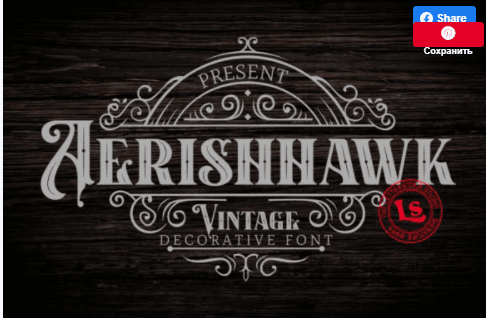
Aerishhawk Font
Aerishhawk - это смелый, отчетливый и невероятно впечатляющий дисплейный шрифт. Добавьте его к каждому дизайну, который требует напористой и элегантной атмосферы, и вы будете поражены выдающимися результатами.